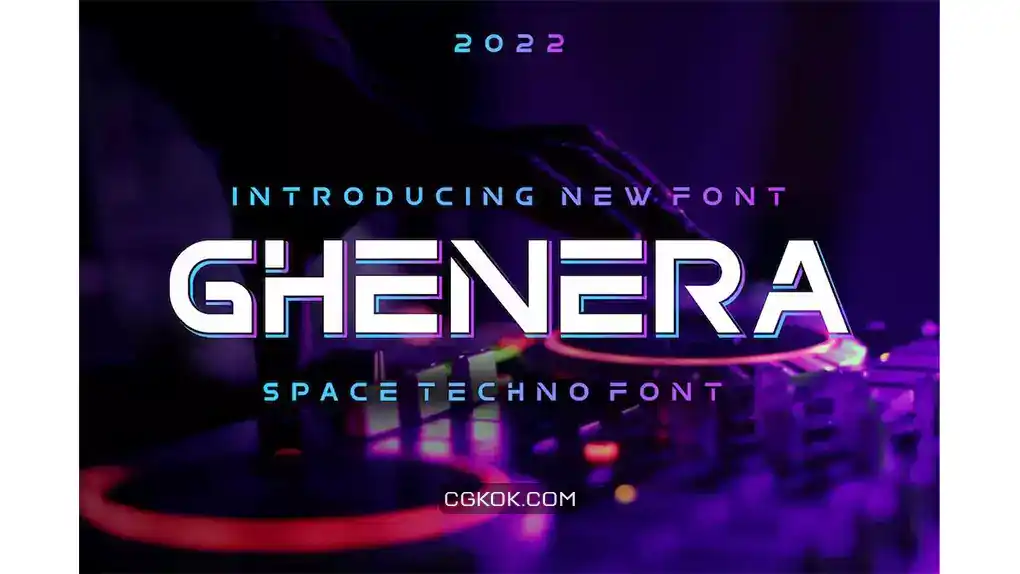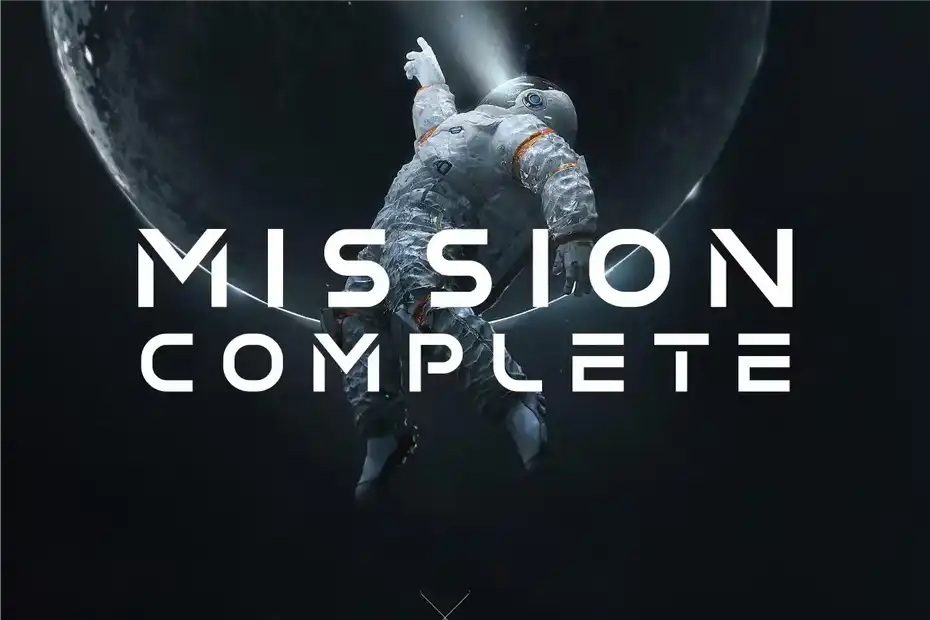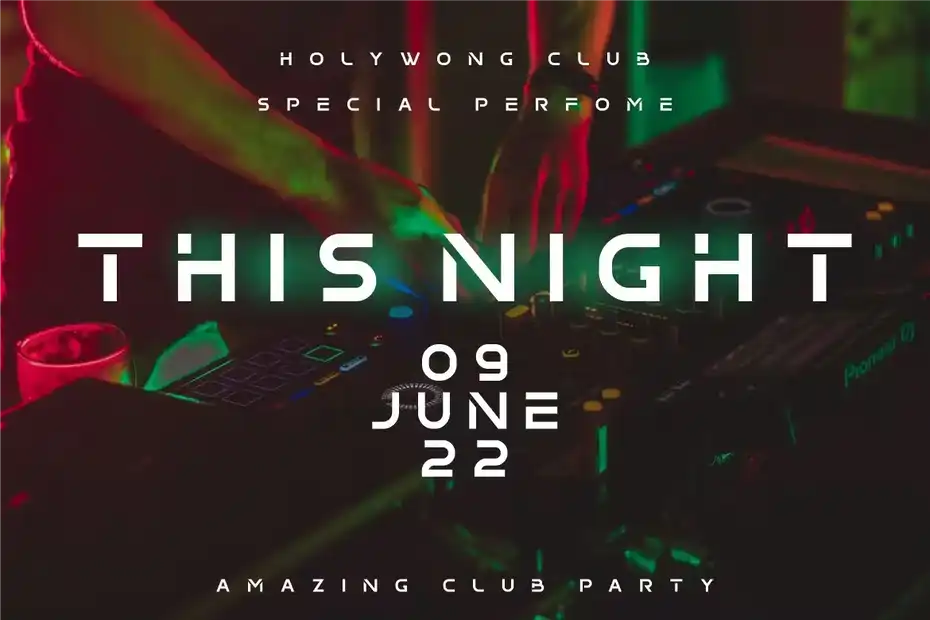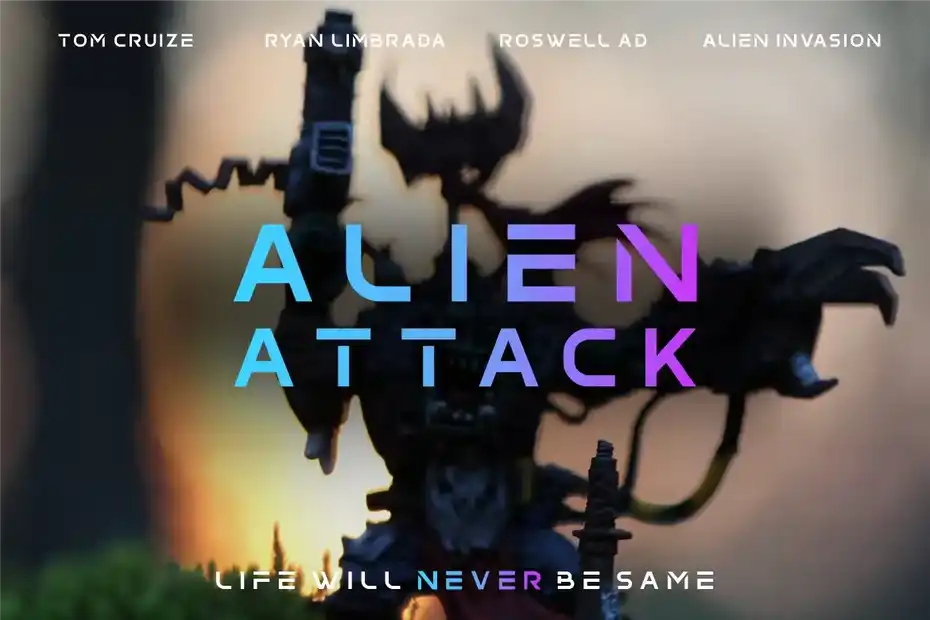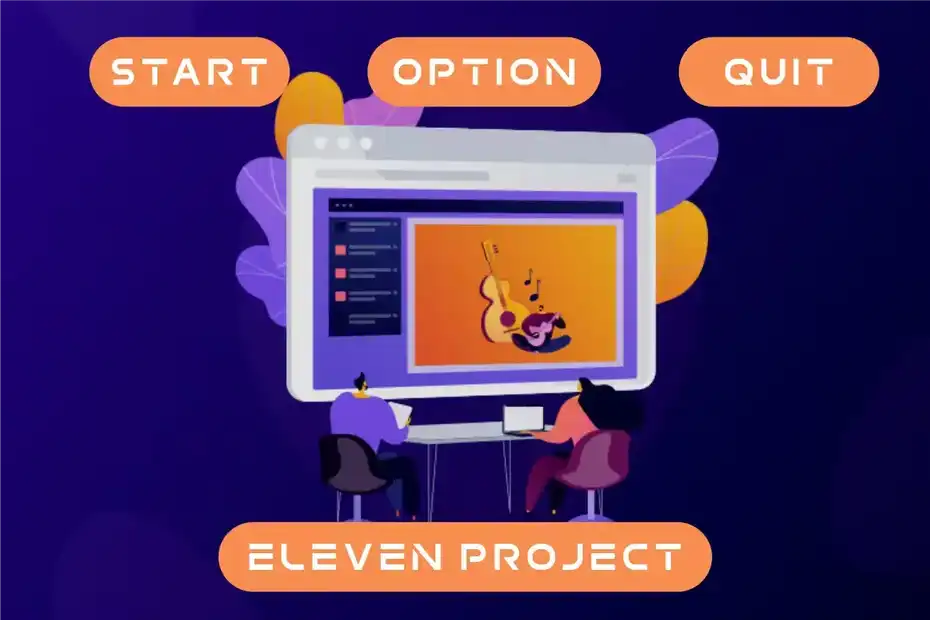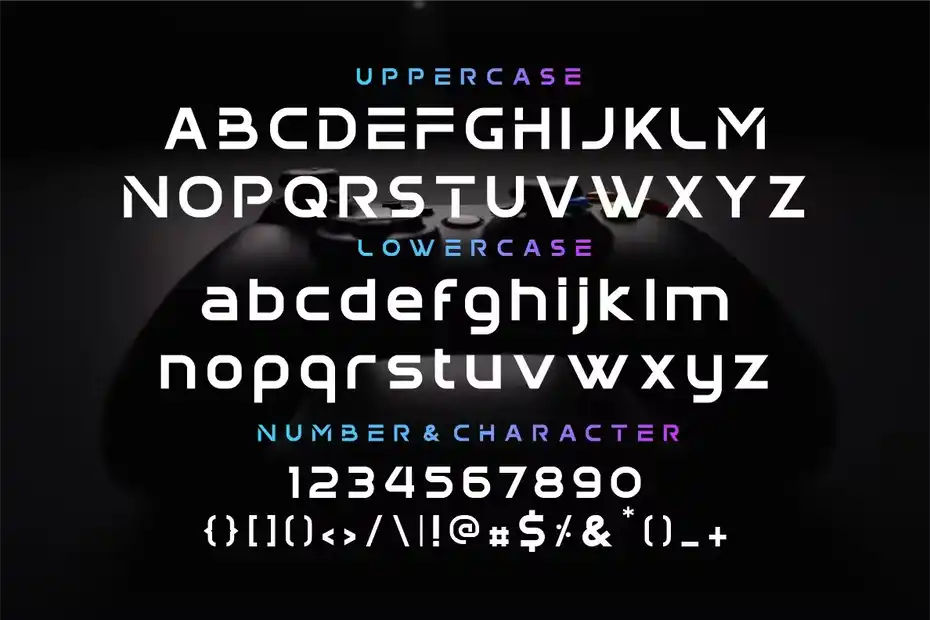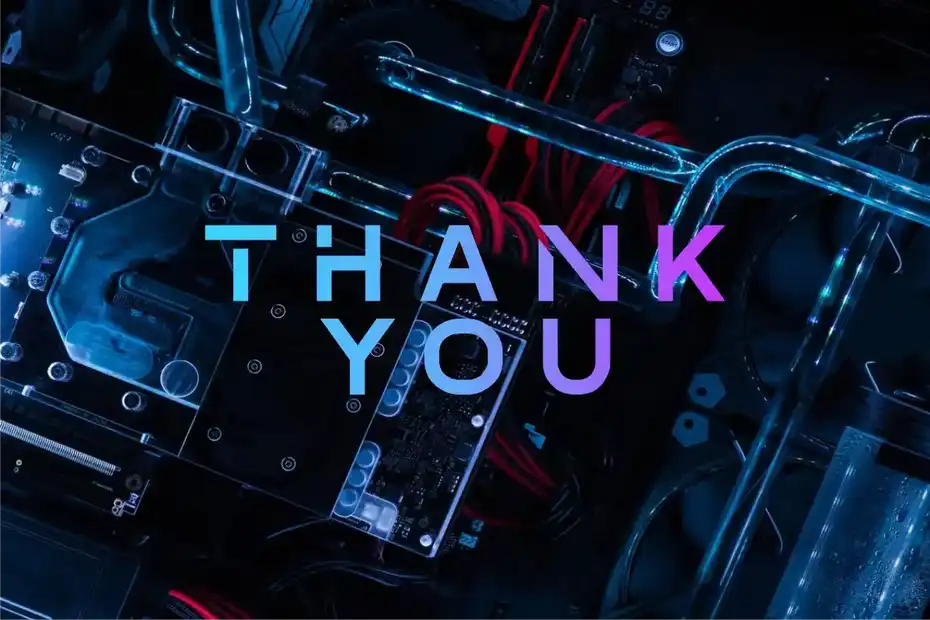
دانلود فونت بازی تکنولوژی Ghenera Techno Font
دانلود فونت بازی تکنولوژی Ghenera Techno Font : این مجموعه شامل یک فونت فانتزی است که برای لوگو، برندینگ، چاپ تی شرت و غیره مناسب میباشد. از دسته بندی دانلود فونت انگلیسی در سیجی کوک می توانید آرشیو کامل فونت های حرفه ای و با کیفیت را مشاهده کنید.